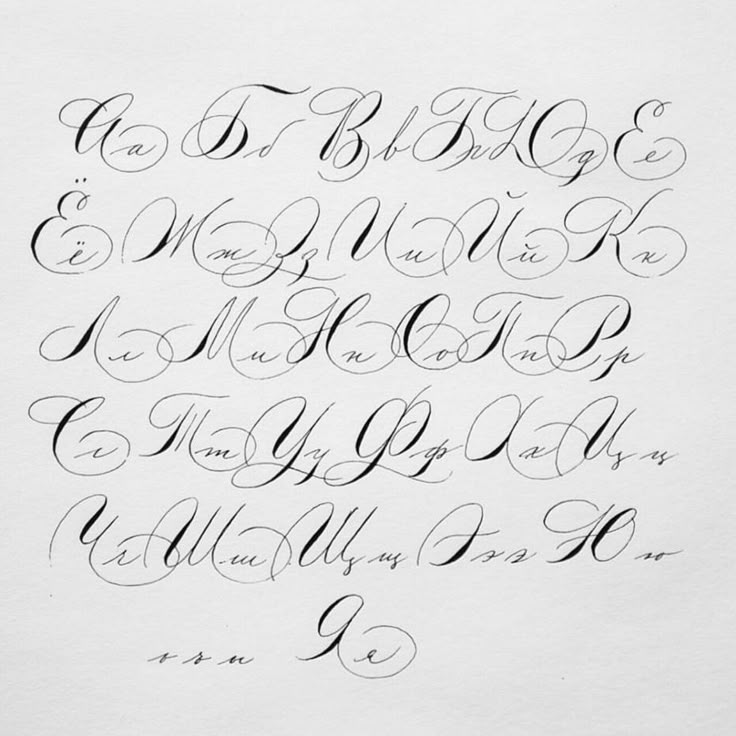
тренды дизайна и брендинга 2022-2023
В 2022 году российские брендинговые агентства погрузились в последствия новой реальности — командам нужно было помочь компаниям оперативно провести импортозамещение, вывести на рынок локальные продукты, разработать «правильный нейминг» и адаптировать «санкционный дизайн» упаковки. Представители индустрии поделились с Sostav перспективами логотипов на кириллице, а рассказали о запросах клиентов и особенностях айдентики в эпоху глобальных перемен.
Локализация на ощупь
Новая реальность повлекла за собой уход с российского рынка многих мировых брендов и рекламодателей. Поэтому в агентствах отметили популярность запроса на импортозамещение: освободившуюся нишу нужно было занять локальными брендами и оперативно вывести локальные продукты на полки.
Этот процесс стал настоящим челленджем для российских креаторов: никогда прежде столь интегрированная в мировой брендинг страна не оказывалось в таком положении. Как добавил Семён Шатыло, креативный директор Depot: «На протяжении многих лет мы были встроены в мировые коммуникационные процессы, адаптация брендов на локальный рынок происходила крайне редко.
Решения с командой клиентов приходилось искать на ощупь — с командами клиента приходилось выстраивать новые стратегии и согласовывать все это со штаб-квартирами».
Адаптация к обстоятельствам происходила стихийно, дизайнеры столкнулись с жестким ограничением в сроках — например, нейминг и бренд «Вкусно — и точка» в ГК «Родная речь» разработали за рекордные три недели. Это отразилось на дизайне: так, в июне продукция сети была представлена в белой упаковке без принта.
Александр Вагин, CEO SUPERMARKET Branding Agency, считает, что пока в большинстве случаев всё выглядит как «затыкание дыр», поскольку в спешке нужно из западного юрлица сделать российское со всеми вытекающими. При этом запросы клиентов варьируются от «сделайте, как было», своего рода «абибас», до полной смены позиционирования и айдентики, добавляет Катя Слободская, арт-директор BBDO Branding.
Александр Вагин, CEO SUPERMARKET Branding Agency:
Мимикрия и копирование бренд-кодов компаний, которые ушли с российского рынка — это путь получения краткосрочной выгоды, который в определённой степени ограничивает возможности развития компании в среднесрочной и долгосрочной перспективе.
Это не стратегично для компаний, которые планируют продолжать работать на российском рынке.
Мир уже не будет прежним — компании осознают, что им нельзя быть такими же, как раньше. Поэтому даже среди локальных компаний значительно возрос спрос на ребрендинг, отметила Алина Ракитина, генеральный директор Autentica. Так, в конце 2022 года «Литрес» решил стать книжной экосистемой и изменил написание впервые за 17 лет своей работы.
Генеральный директор Getbrand Андрей Горнов считает, что в 2023 году брендинг сам по себе окажется максимально востребованным: «Те, кто пытается закрыться от этого и говорит, что времена сложные, сейчас не до брендинга, просто сгинут с рынка или превратятся в производителей СТМ за небольшую рентабельность».
Сергей Калинчук, генеральный директор DDC.Group:
Я не думаю, что отрасль брендинга испытает серьёзные проблемы в связи с уходом иностранных компаний и эмиграцией части сотрудников. Мы и так работали в основном с российскими производителями, а ковид приучил нас к удалёнке.
Кардинального роста нашей индустрии прогнозировать не буду: речь сейчас идёт о смене клиентов, а не о добавлении новых клиентов к старым. Одни уходят, другие приходят — в сумме результат такой же.
Новая реальность — новый формат работы
В брендинговых агентствах в качестве тренда уходящего года выделили смену привычного формата работы: у компаний нет времени на бесконечную череду долгих согласований и принятие решений. Поэтому в проектах как никогда важна скорость — этапы реализации кейса стали ещё сильнее дробиться в короткие спринты.
Кроме того, дизайнеры активно выполняли роль ментора — проводили обучающие воркшопы для бренд-команд, а также разрабатывали инструменты для оптимизации работы на стороне клиента.
Артём Митин, операционный директор Human Code :
Год от года мы видим рост интереса к стратегии в брендинге. При том не только со стороны клиентского рынка, но и среди агентств возникает всё большее желание разбираться в основах и сути бренда.
Кириллица: не тренд, а факт
Уход зарубежных брендов, рост локальных производителей и активное продвижение политики автономного пути России от глобального мира отразились на нейминге. «Если раньше мы могли сделать русский бренд и использовать латиницу, и это гармонично встраивалось, то сейчас, если мы говорим про российский бренд, встаёт вопрос: «А как мы должны называться?»», — описывает ситуацию Валерия Репина, СЕО и креативный директор Repina branding .
Одним из сценариев в российском брендинге станет русификация для позиционирования локальной природы бренда и игра на национальных настроениях, считает Антон Евдокимов, креативный директор 19agency84. Если раньше логотипы на латинице скрывал намерения брендов вывести продукты на международный рынок, сейчас эта опция отпала сама собой, рассказывает Владимир Лифанов, основатель и креативный директор Suprematika.